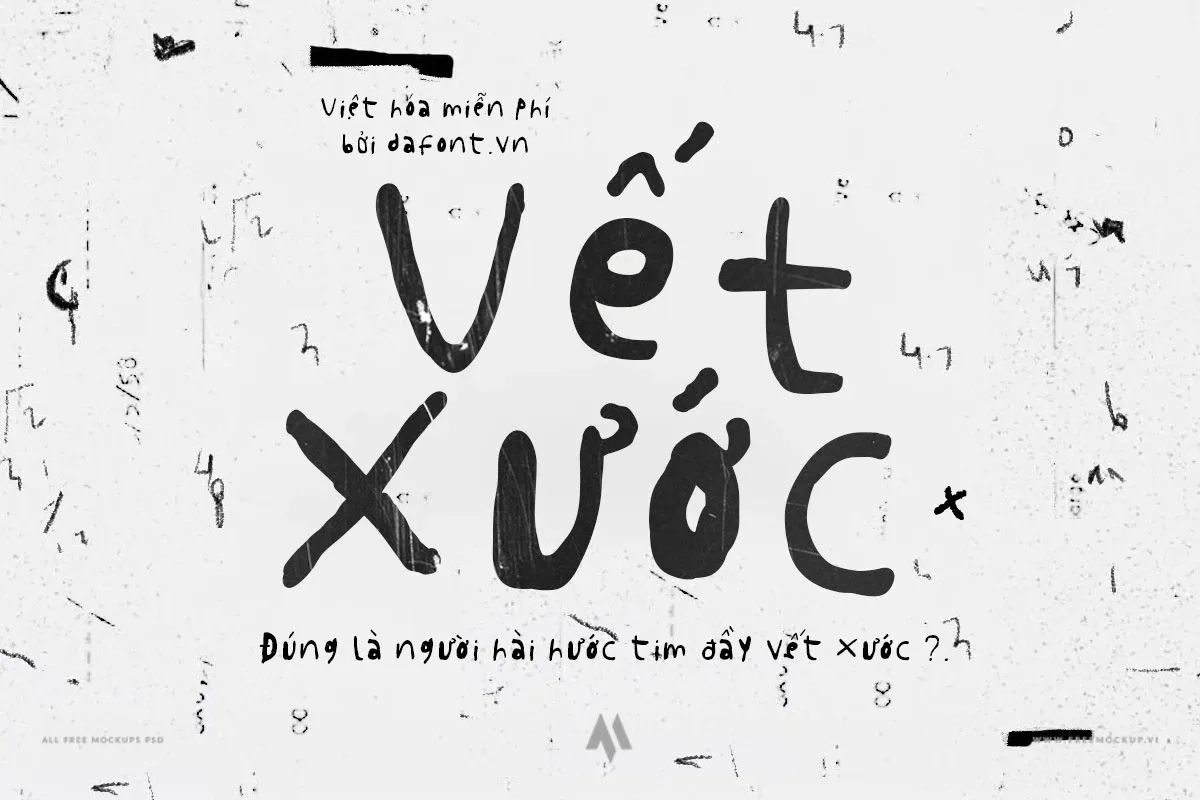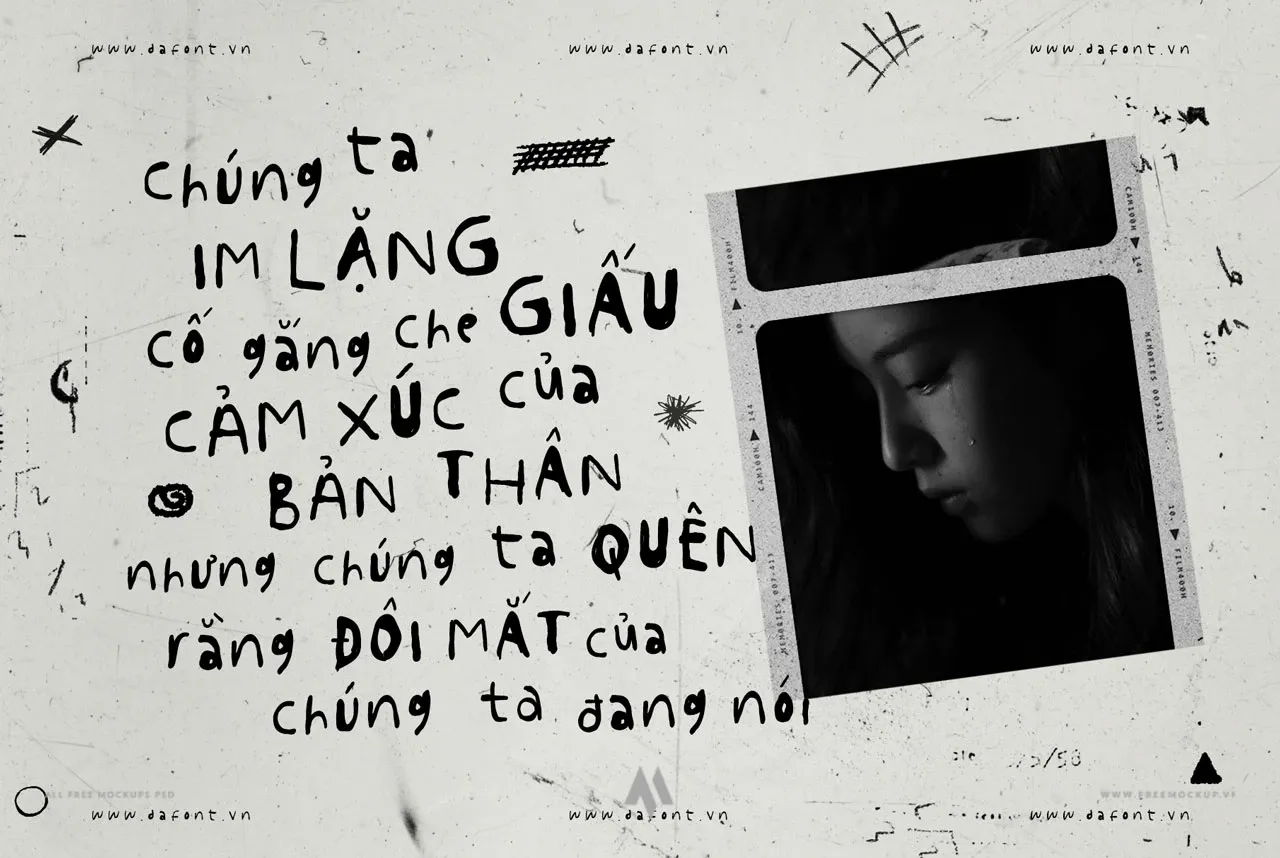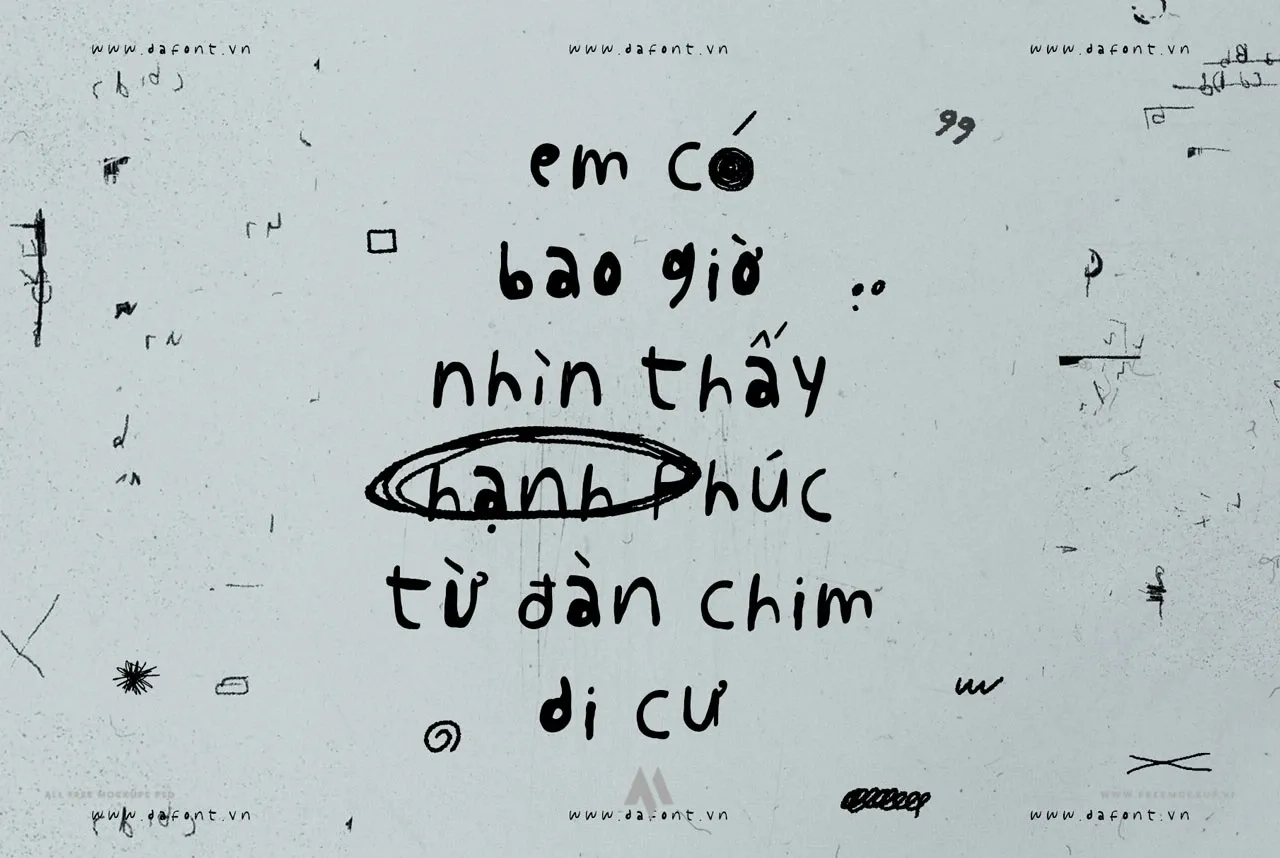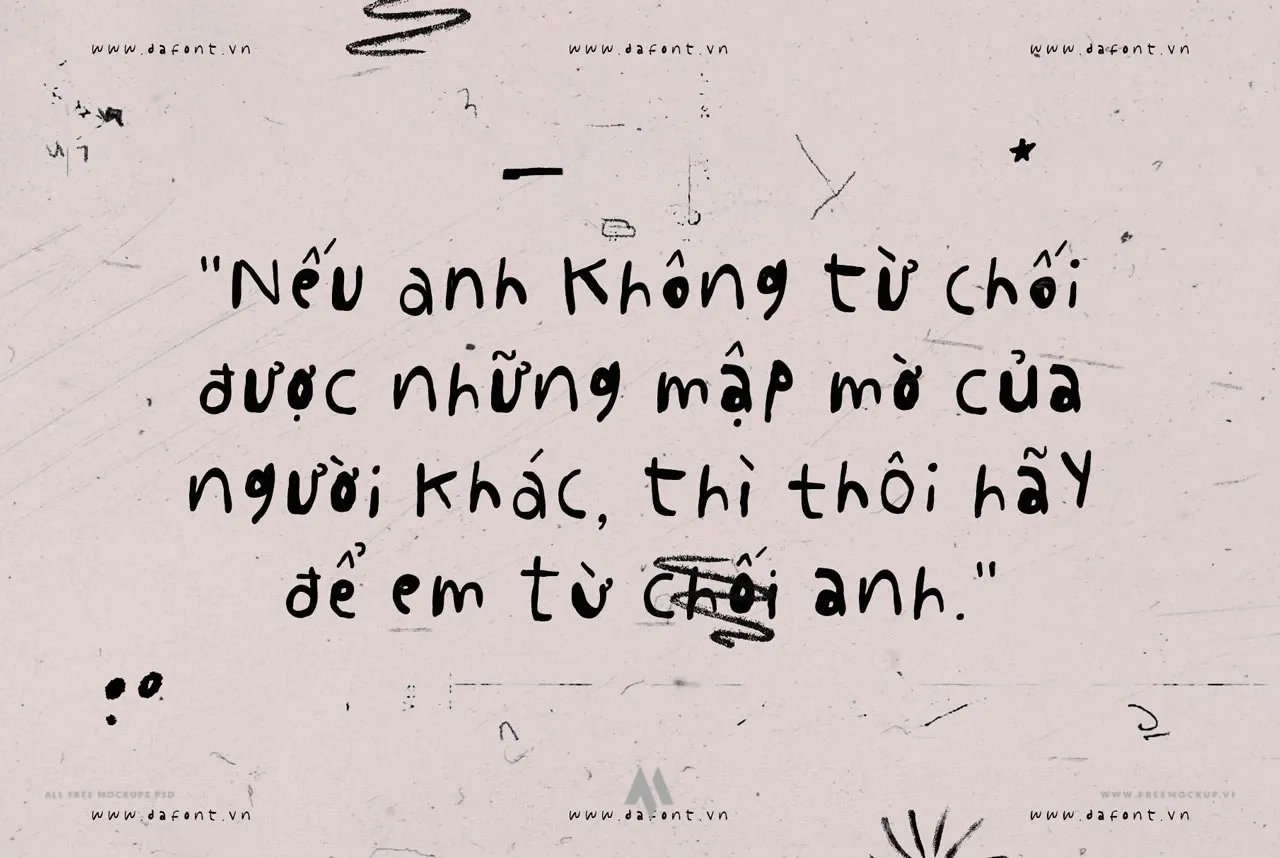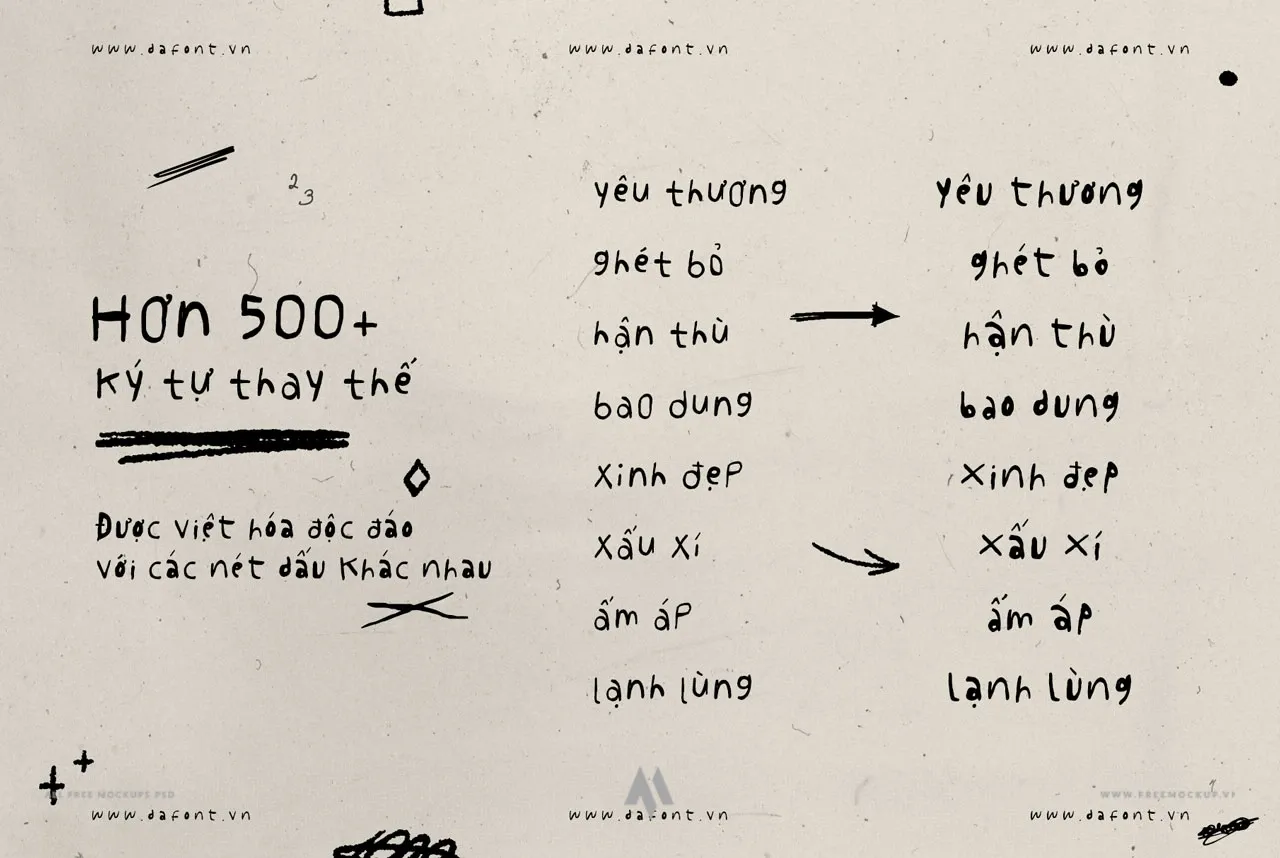
DFVN Corose Việt Hóa là bộ font chữ viết tay (Handwritten Script) mang đậm chất nghệ thuật thủ công, dung hòa trọn vẹn giữa vẻ đẹp thẩm mỹ tinh tế và cảm xúc tự nhiên, mộc mạc. Lấy cảm hứng từ nét bút mực chân thực trên trang giấy, từng ký tự sở hữu sự biến tấu ngẫu hứng, phá cách, giúp tác phẩm thiết kế thoát khỏi khuôn mẫu cứng nhắc và trở nên sống động, cuốn hút.
Đặc điểm nổi bật
- Nét bút thủ công sống động: Đường nét mềm mại, uyển chuyển với độ bất quy tắc có chủ đích, tái hiện chân thực cảm giác chấp bút tự nhiên trên từng trang giấy.
- Cá tính độc đáo & Tinh xảo: Mỗi con chữ được trau chuốt tỉ mỉ, tạo chiều sâu thị giác khác biệt hoàn toàn so với các phông chữ kỹ thuật số thông thường.
- Việt hóa chuẩn mực & Tự nhiên: Hệ thống dấu tiếng Việt được xử lý linh hoạt, chuẩn tỷ lệ và giữ trọn vẹn phong cách phóng khoáng của nét chữ viết tay thật.
Ứng dụng đa dạng trong thiết kế
- Ấn phẩm sự kiện & Quà tặng: Thiệp cưới phong cách lãng mạn, thiệp chúc mừng, bưu thiếp nghệ thuật, thư mời và phong bì thư.
- Nhận diện thương hiệu & Bao bì: Logo cá nhân, typography cho studio nghệ thuật, tiệm hoa, nhãn mác mỹ phẩm hữu cơ, nến thơm và bao bì quà tặng thủ công.
- Xuất bản & Sáng tạo: Bìa sách, tiểu thuyết nghệ thuật, thơ ca, lookbook thời trang và trích dẫn truyền cảm hứng (quotes).
- Truyền thông số: Banner quảng bá sự kiện, hình ảnh visual cho mạng xã hội và typography trên ảnh phong cảnh, du lịch.